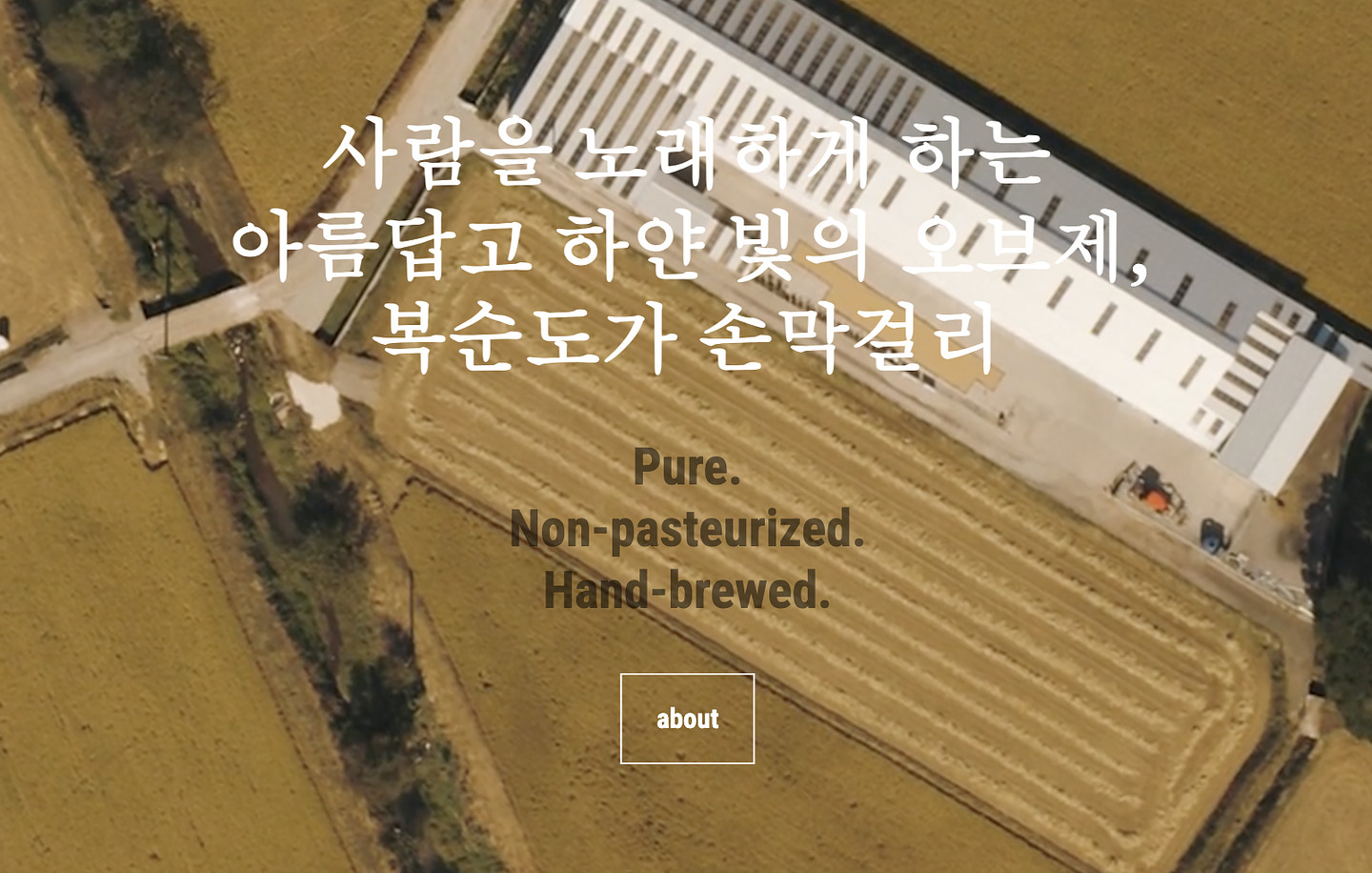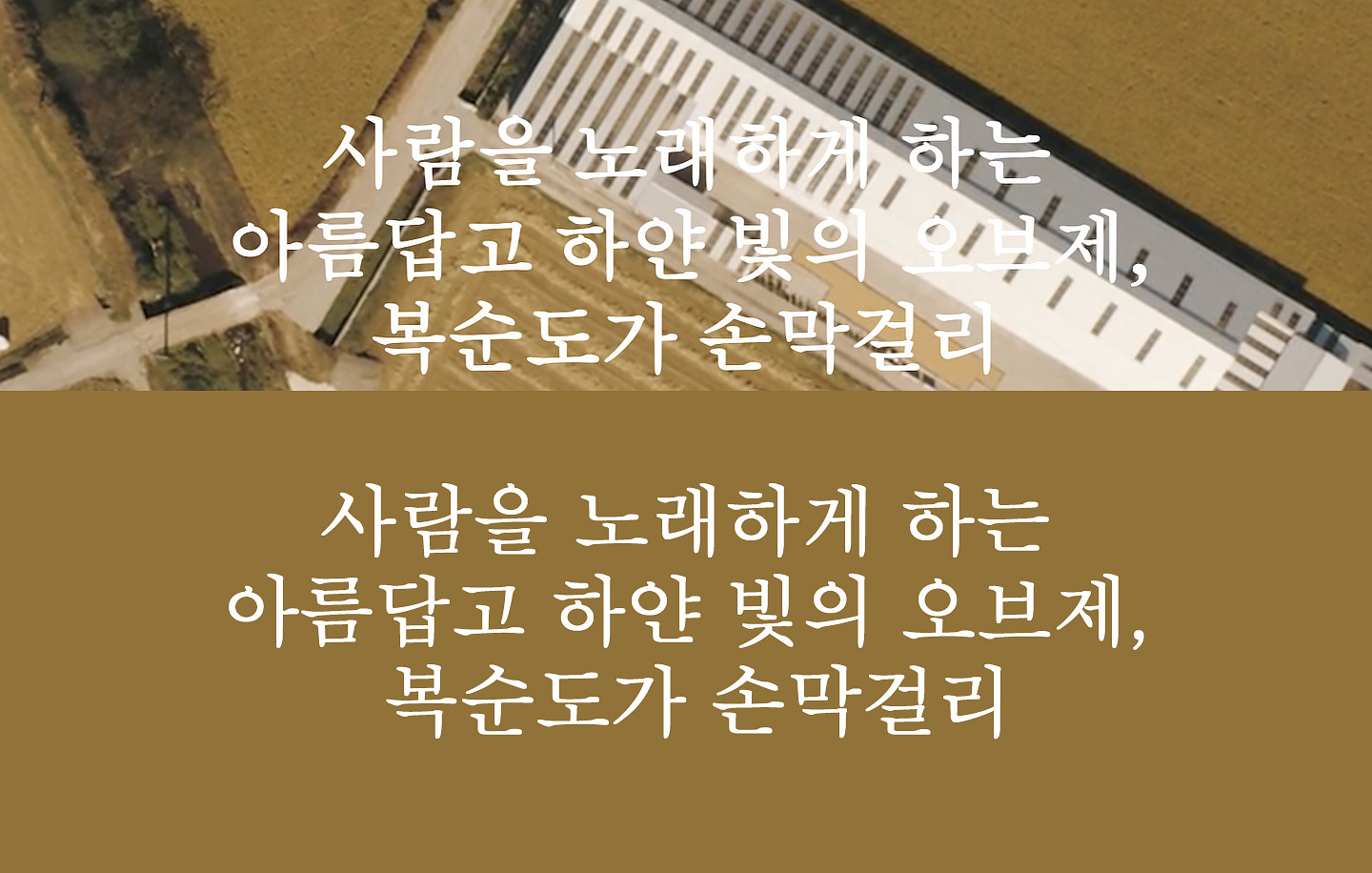
'사람을 노래하게 하는 아름답고 하얀 빛의 오브제, 복순도가 손막걸리' 에서 쓰이는 폰트가 무엇인가용..?? 뭔가 자주본거같은데 모르겟어여ㅠㅠ 도움을 부탁드립니다..
바탕
윈도우에 내장된 기본 폰트인 바탕(한컴바탕X, 바탕체x, 바탕O)을 굵기, 행간, 자간 조정해서 사용한 것 같아요.(이미지는 바탕 레귤러+볼드효과)